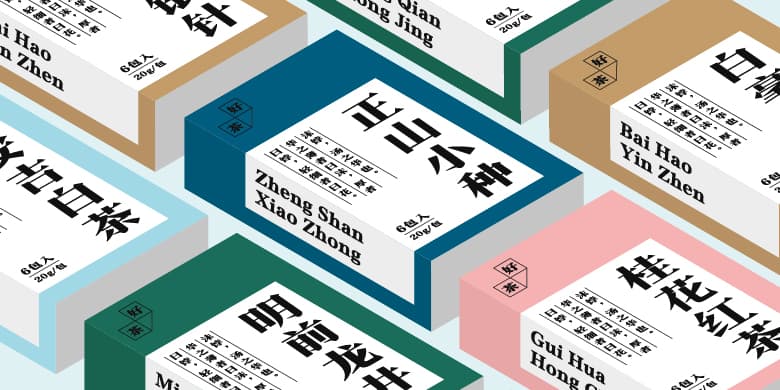
品牌:方正字库设计师:苏士鹏发行时间:2021字库编码:大陆简体(GB2312-80)分类:宋体字体属性:精品字
方正雕刻版,受徐冰老师《析世鉴》的启发创作而成,该字获得第三届『方正奖』中文专业优秀奖。这是一款现代感与古典风相结合的宋体,稳健独特的风格显得放松又自在,以字形向右倾斜来展示力量感,横细竖粗的形态比例体现柔中带刚、端庄稳重又不失活泼的视觉体验。适用于书籍排版、视频海报、产品包装及周边领域。